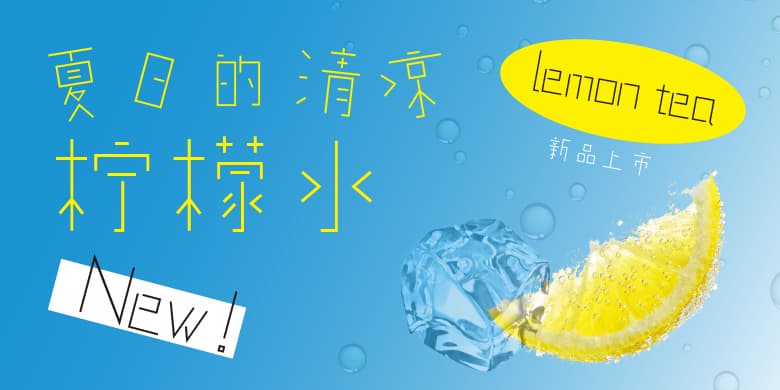
品牌:个人字库设计师:李佛君发行时间:2021字库编码:大陆简体(GB2312-80)分类:创意字体字体属性:精品字
作品以线条为缘起,以抽象几何手法,构筑极简唯美的城市建筑意象,除横平竖直的基础表现,融入45度斜角展开的线条,在保证识别性的基础上减化笔画,归纳出易于表现为几何造型的结构,形成结构独特、识别效果突出、极具时尚感的字型,契合互联网时代个性鲜明的传达需求,提供独具一格的视觉传播解决方案。
品牌:个人字库设计师:李佛君发行时间:2021字库编码:大陆简体(GB2312-80)分类:创意字体字体属性:精品字
作品以线条为缘起,以抽象几何手法,构筑极简唯美的城市建筑意象,除横平竖直的基础表现,融入45度斜角展开的线条,在保证识别性的基础上减化笔画,归纳出易于表现为几何造型的结构,形成结构独特、识别效果突出、极具时尚感的字型,契合互联网时代个性鲜明的传达需求,提供独具一格的视觉传播解决方案。